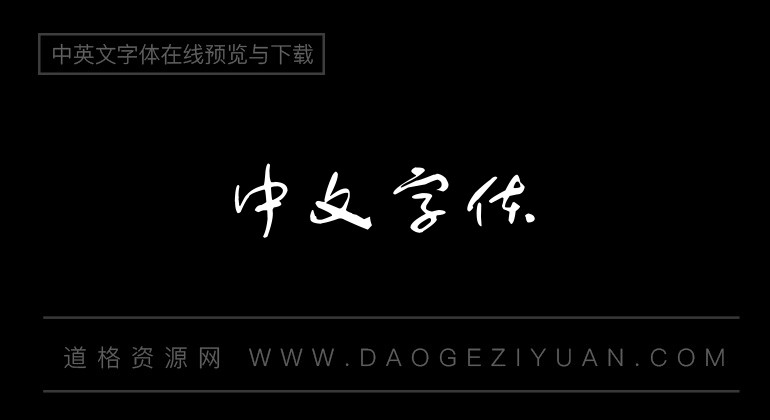
书体坊于右任字体
书体坊于右任字体是一款清新、优雅的中文字体,由书体坊设计师曾于右设计,具有清新的风格,拥有优雅的线条,淡雅的色调,可以给文字以深邃的感觉。书体坊于右任字体的字形设计简洁大方,笔画优美流畅,非常适合用于报刊、书籍、广告等多种印刷品的设计。
书体坊于右任字体是一款非常不错的手写艺术字体,具有很好的视觉感,适合于文化类的宣传设计、商业类品牌的广告和产品包装设计以及个性化文字排版等较多场景。